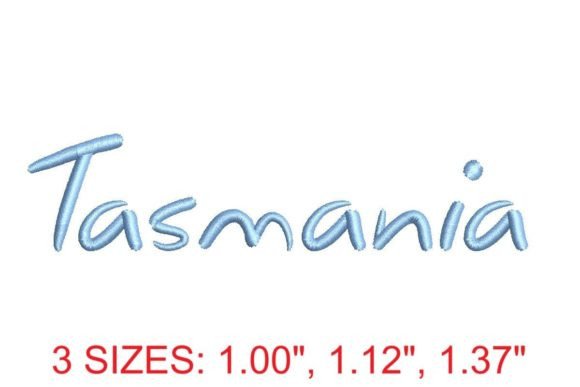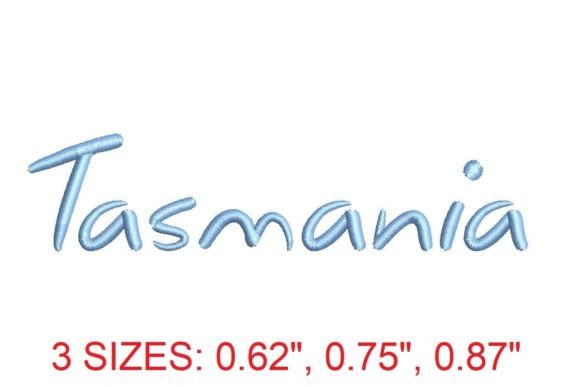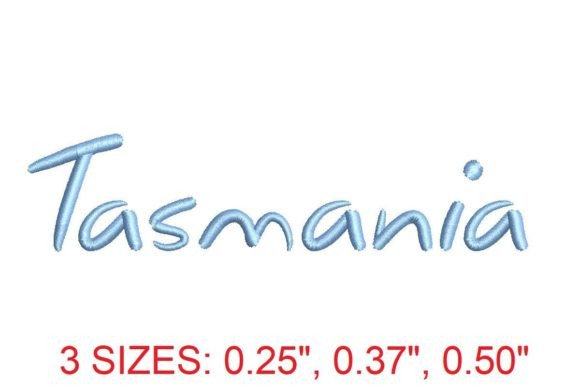
Tasmania Font
Пошук відповідних елементів дизайну може бути складним, але Tasmania Font пропонує виняткову колекцію, яка миттєво покращить вашу роботу.
Незалежно від того, чи створюєте ви продукти POD (друк на вимогу), весільні запрошення або графіку для соціальних мереж, Tasmania Font стане ідеальним вибором.